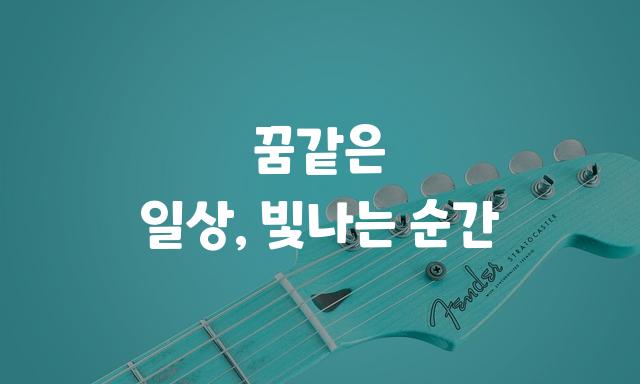
원스토어 모바일고딕 제목체는 꽉 찬 느낌의 기본 고딕 스타일로, 제목용으로 최적화되어 강력하고 명확한 메시지 전달이 가능합니다. 뚜렷한 라인과 균형 잡힌 구조가 특징입니다.
원스토어 모바일고딕 제목체은(는)
기본 고딕, 굵은 고딕, 감성적인, 단단함, 부드러움, 길고/크고 계열의 생김새를 가지고 있으며
로고 디자인, 광고 캠페인, 웹/앱 디자인 등에서 자주 활용되며, 효과적인 메시지 전달에 적합합니다.
이 폰트는 광고/마케팅, 크리에이티브, 기술/IT 분야에 잘 어울리며,
세련된, 명확한, 전문적인 느낌을 담고 있는 것이 특징입니다.